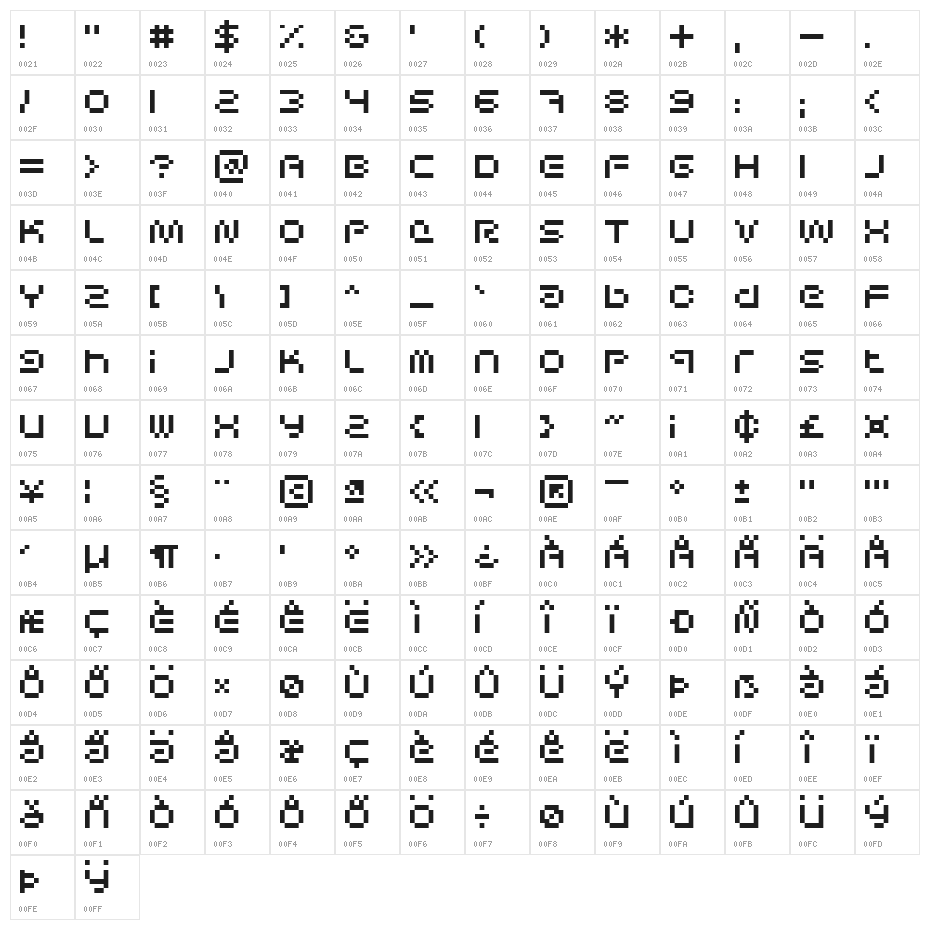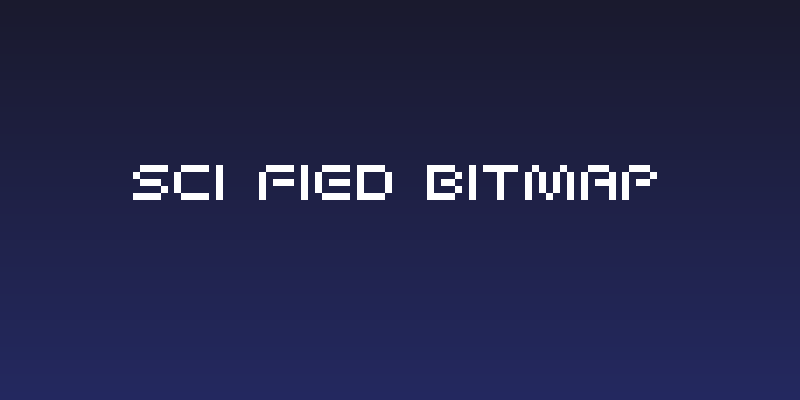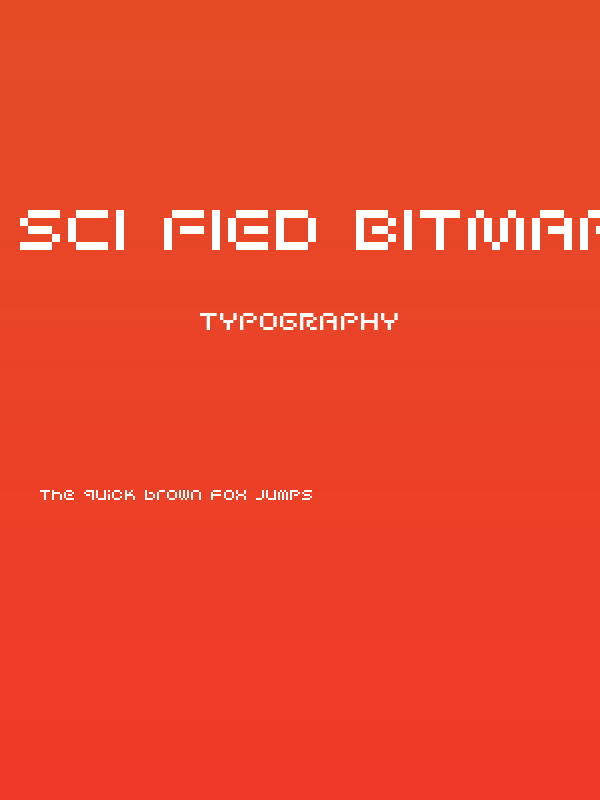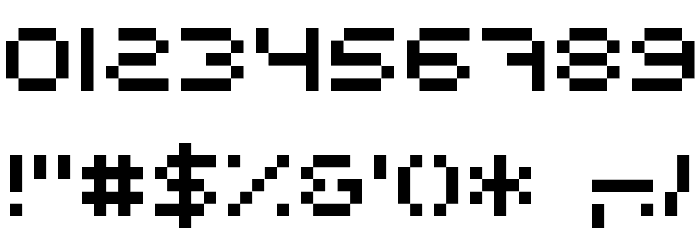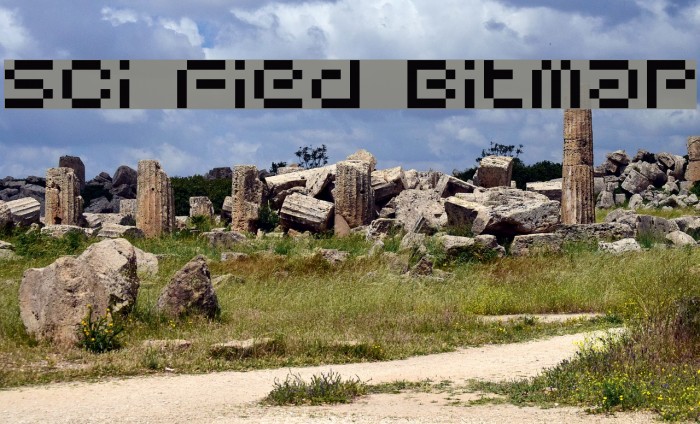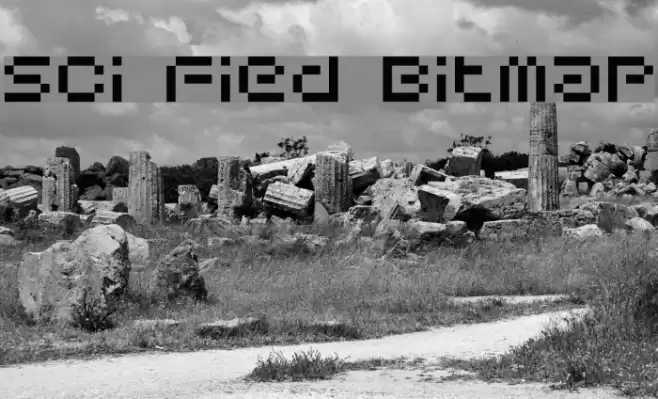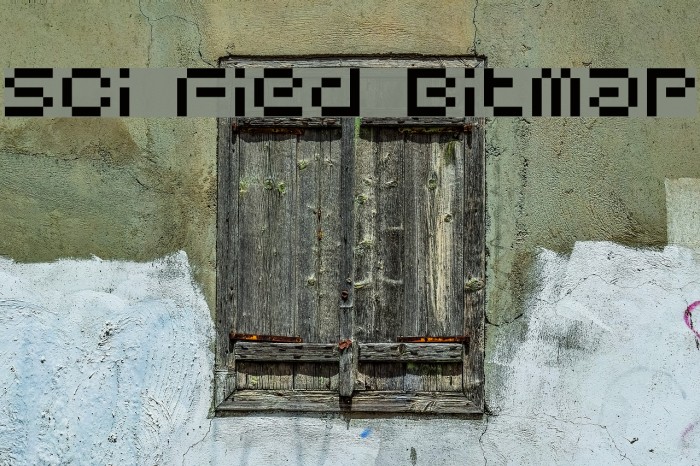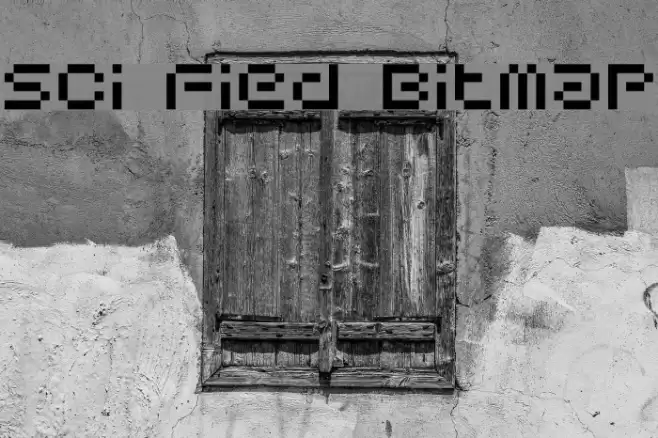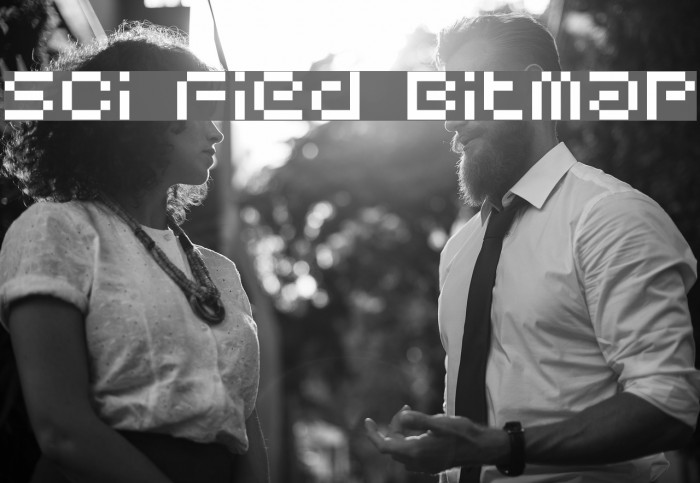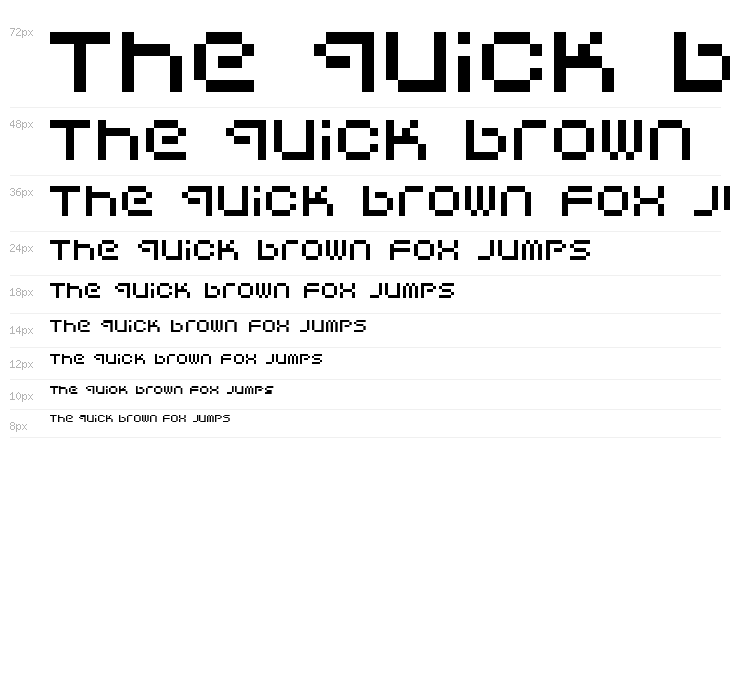
Sci Fied Bitmap Font
| Gesamtstil | Retro, Digital |
| Vorgeschlagene Projekte | Perfect for video game designs, tech-themed posters, digital art, and retro-inspired branding. |